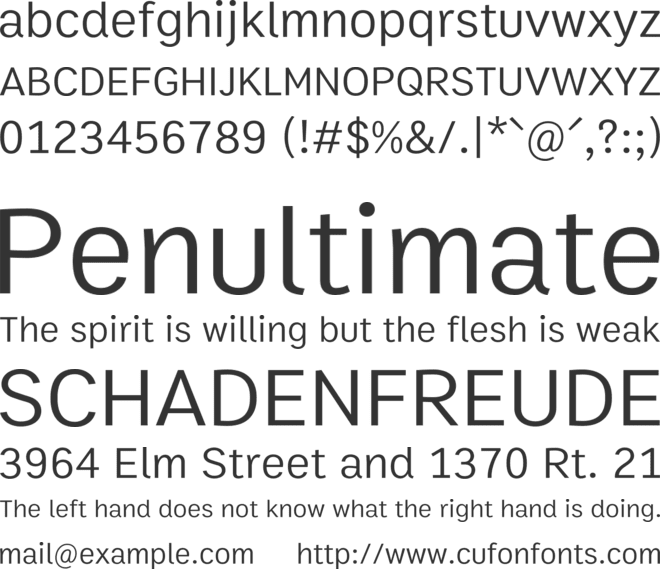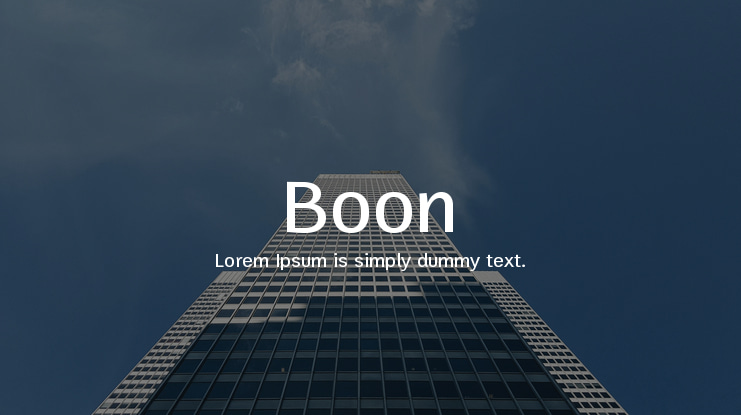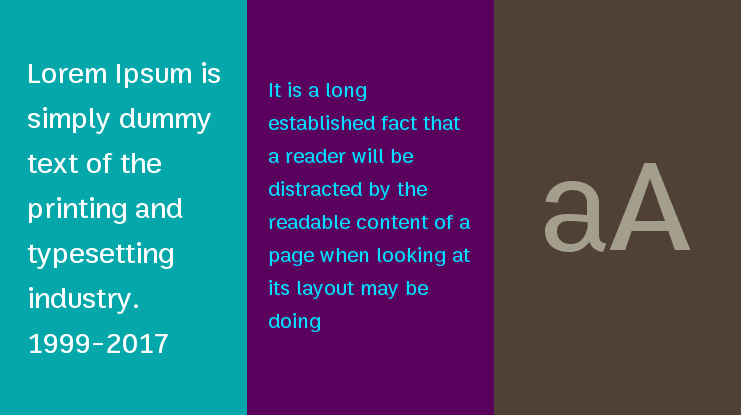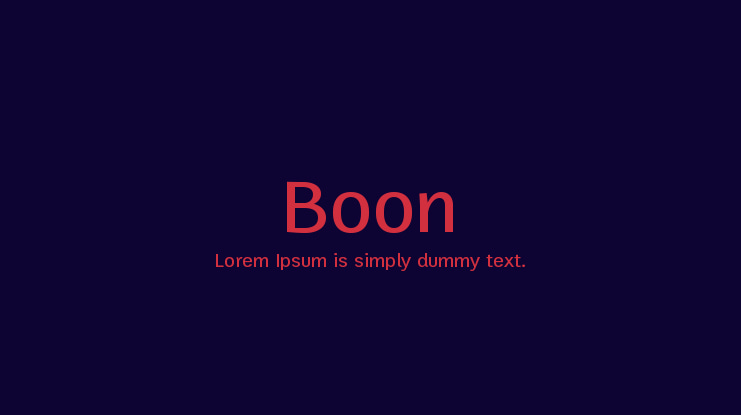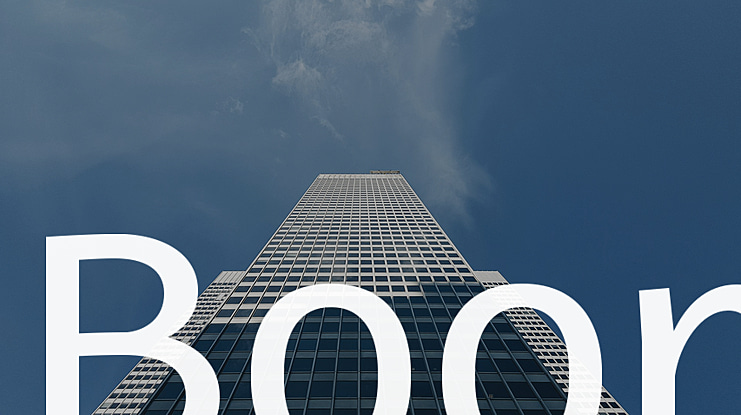
Boon Font Family
Sungsit Sawaiwan
Copyright 2013-2015, Sungsit Sawaiwan description: บุญ คือ ชุดตัวอักษรตระกูลหนึ่ง (font family) ที่มุ่งแสดงผลการจัดเรียงตัวอักษรไทยให้ถูกต้องในเว็บบราวเซอร์ ตัวอักษรทุกตัวทั้งไทย, ละติน และลาว นั้นวาดขึ้นจากรูปทรงเลขาคณิตเพื่อความเรียบง่าย โดยตั้งใจให้สามารถใช้งานได้ดีทั้งส่วนที่เป็นยูเซอร์อินเตอร์เฟสและส่วนที่เป็นเนื้อความ